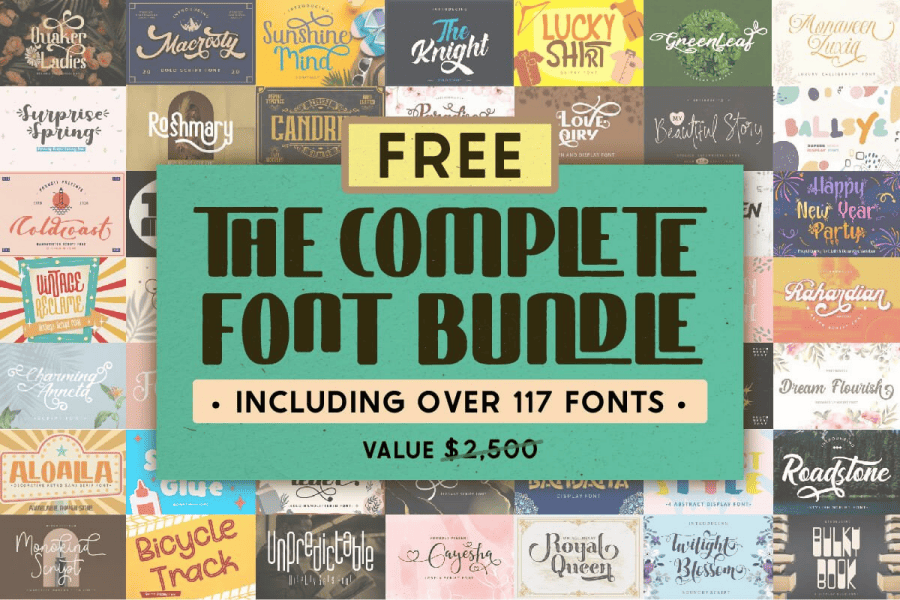
限時免費 The Complete Font Bundle 價值超過 80000 元台幣 117 款英文字型
英文字型永遠不嫌少,只要你能跟上!這次字型合集 The Complete Font Bundle 有夠有夠划算,總共 117 款英文字型,價值 2515 美元,台幣價值超過 80000 台幣,你只要輕鬆登入即可免費下載,包含有復古字體、手寫字體和可愛的字體,尤其美編與小編們都不能錯過,而且可以商業使用,請大家把握限時免費的好時機唷!
△ 以上是這次活動檔案的所有字型一覽,提供給大家參考,也請把握下載的好機會。